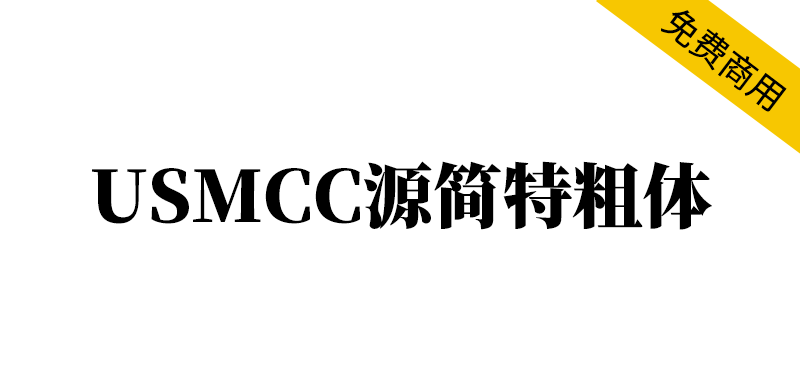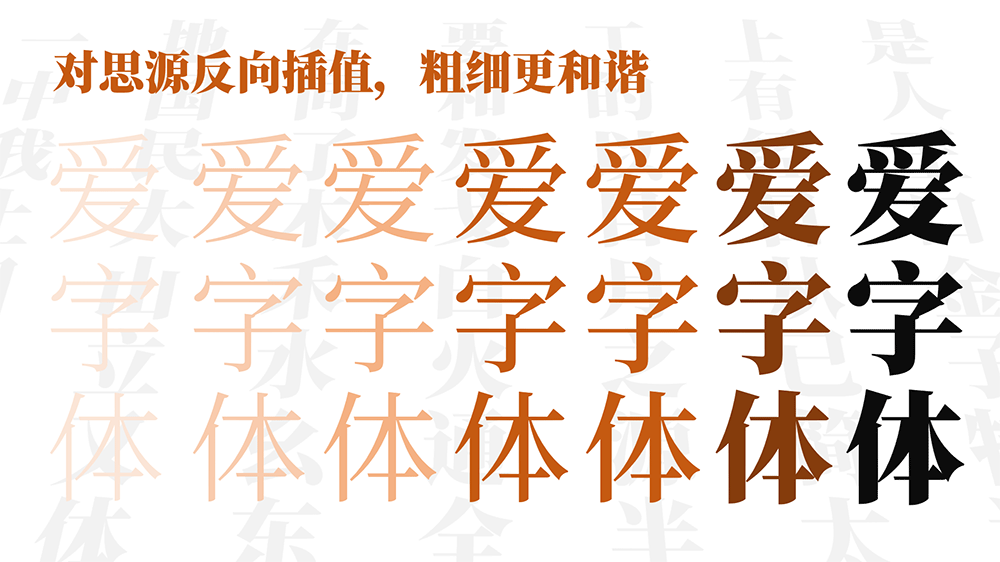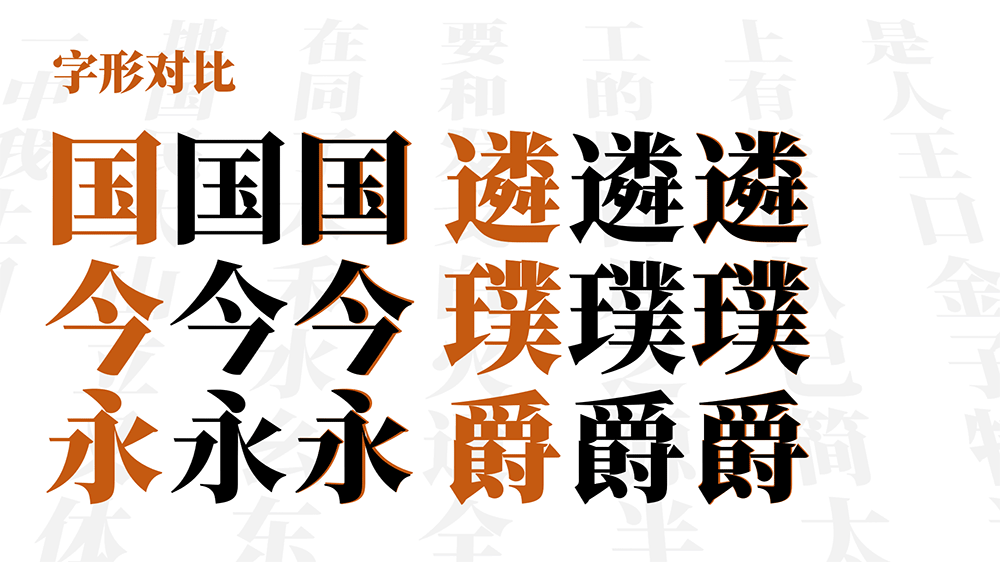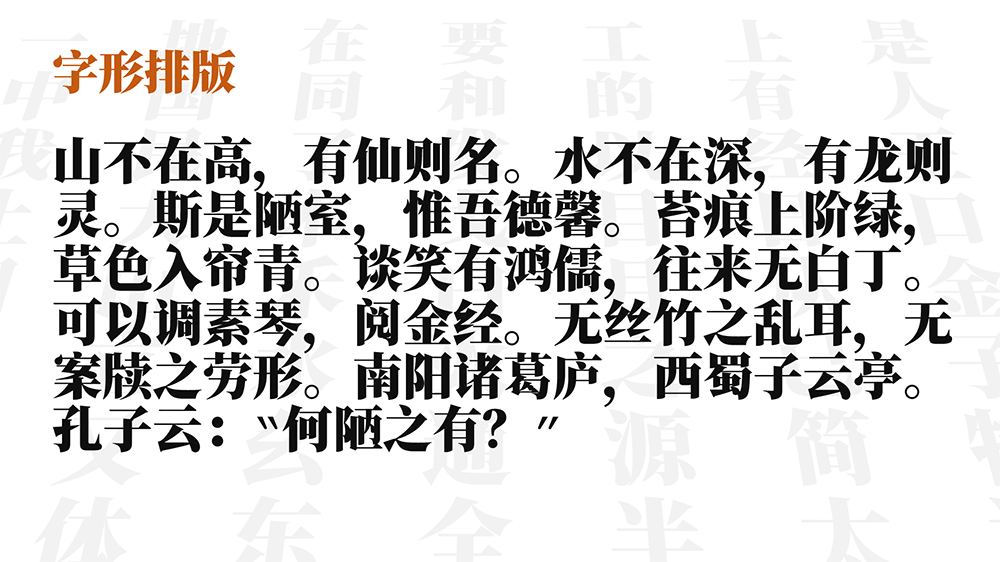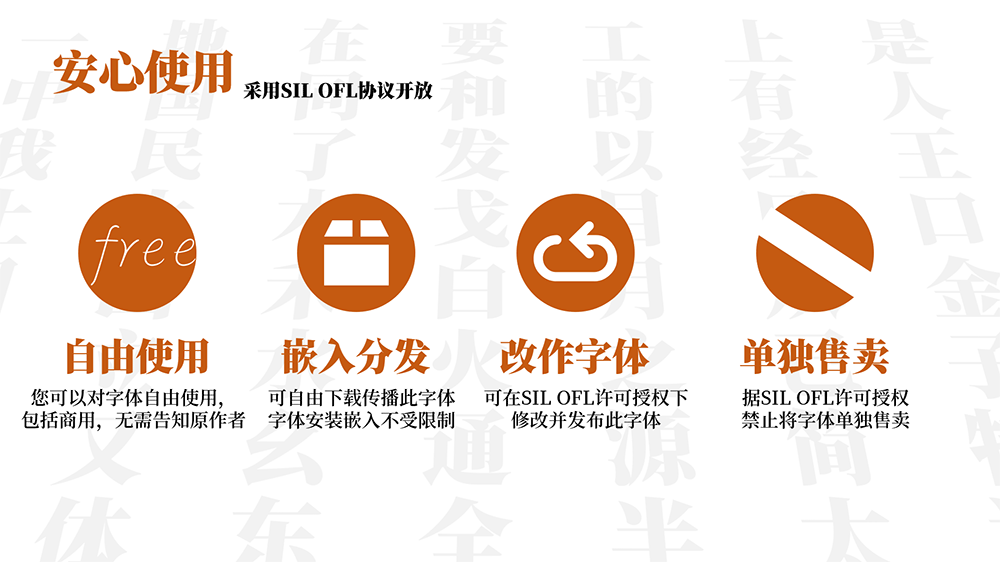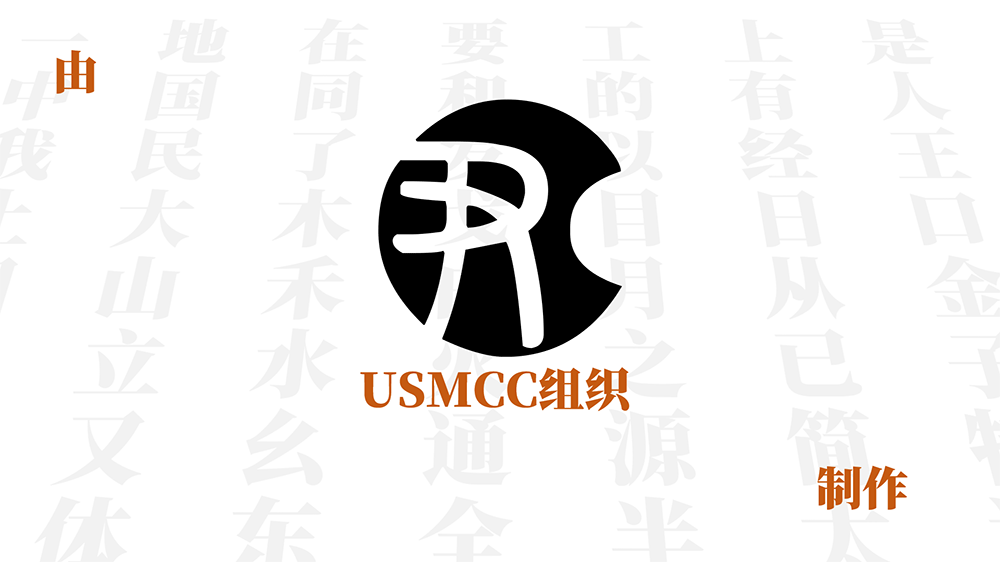
【USMCC源简特粗体】由思源宋体反向插值制作的新字体
还在为标题字体发愁?一款由思源宋体“反向插值”而来的特粗体横空出世!它不仅能与原字重完美搭配,更以SIL OFL协议授权,让你个人和企业都能永久免费商用,彻底告别字体版权困扰。
【USMCC源简特粗体】由思源宋体反向插值制作的新字体
USMCC源简特粗体是由思源宋体反向插值制作的新字体,适用于标题等场所,可以较为和谐的和原有思源字重配合。